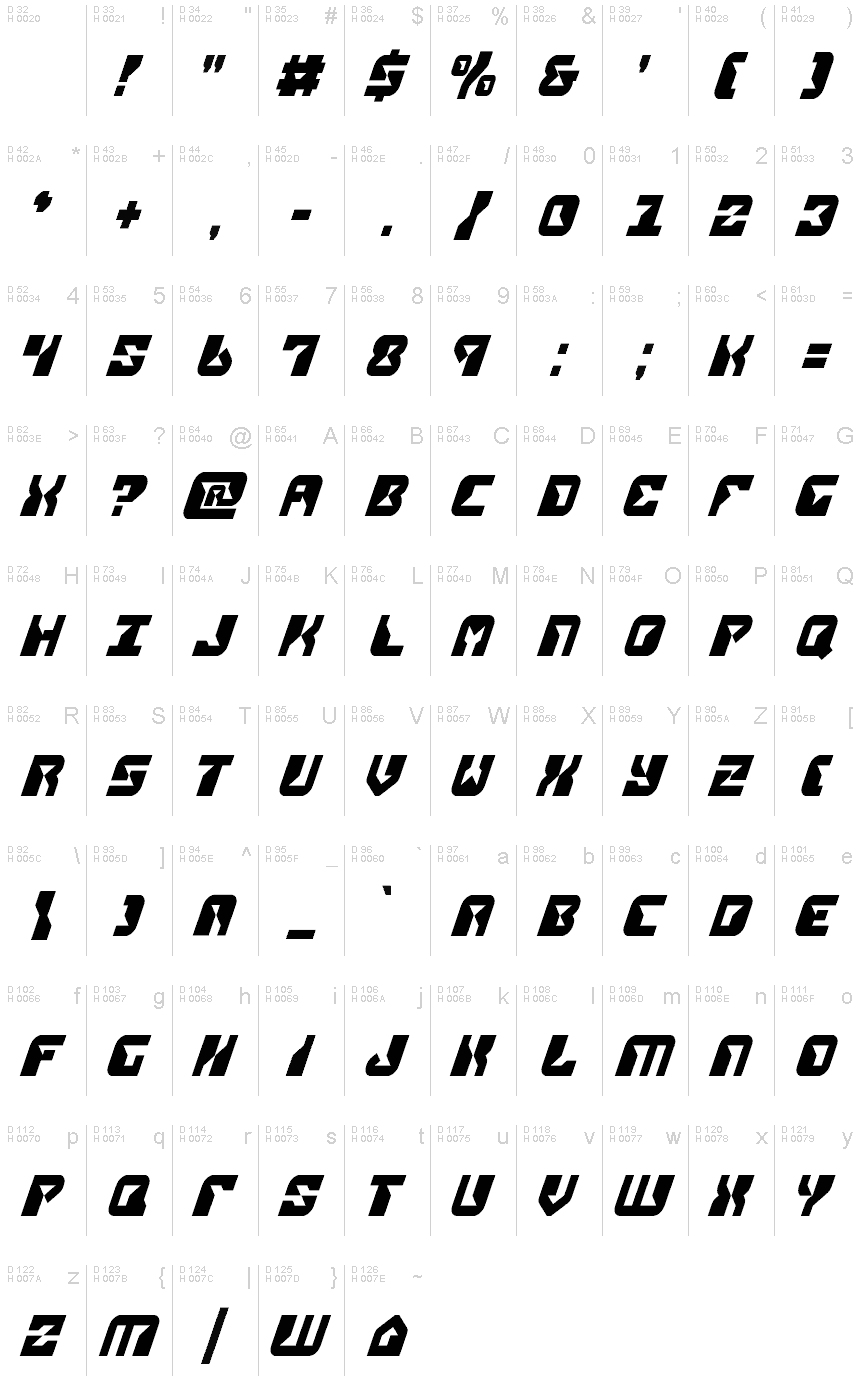
Replicant Condensed Italic od Iconian Fonts to darmowy techniczny font typu display o ostrym, sci-fi charakterze. Litery pochylają się do przodu, mając grube, kanciaste kształty, a powtarzające się trójkątne wycięcia nadają wersalikom maszynowy, syntetyczny wygląd, który kojarzy się bardziej z futurystycznym pościgiem niż z gładką technologią korporacyjną.
Użyj go do logotypów gier, nagłówków na plakatach, okładek albumów, plansz tytułowych czy miniaturek w streamingu, gdzie potrzebujesz darmowego kroju pisma z dynamiką i ostrym, cyfrowym pazurem. Sprawdzi się także w krótkich hasłach brandingowych czy monogramach, ponieważ cięte kształty wewnętrzne i stromy kąt nachylenia sprawiają, że nawet krótkie słowa wyglądają na naładowane energią i będące w ruchu.